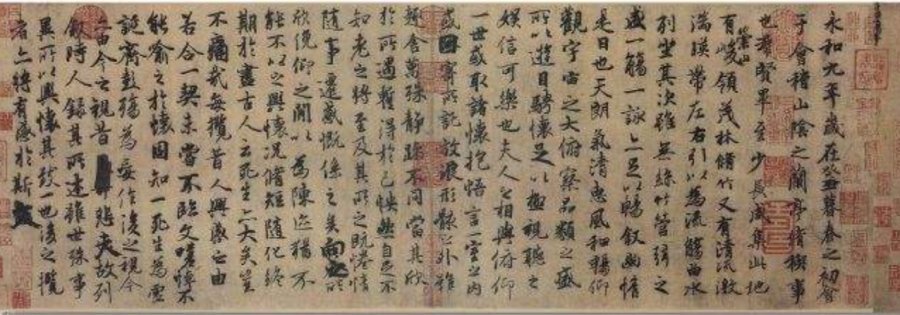
说白了字如其人,就是指书法名家与他的著作类似即创作者的性格特征,字的设计风格接近彻底类似,例如创作者高大魁梧且身型显胖,那麼他的字一般 是豪爽、粗犷,线框雄浑丰满,瘦者则线框苗条等。字如其人,是有科学论证证实的,不但是书法名家的著作字如其人,平常人书写也是如此,只不过是他与书法名家的有所区别,由于手写是人的大脑的形态意识根据手转为笔,换句话说,把手脑的形态意识转到笔端,那麼,哪些的形态意识便反映哪些的笔迹来。
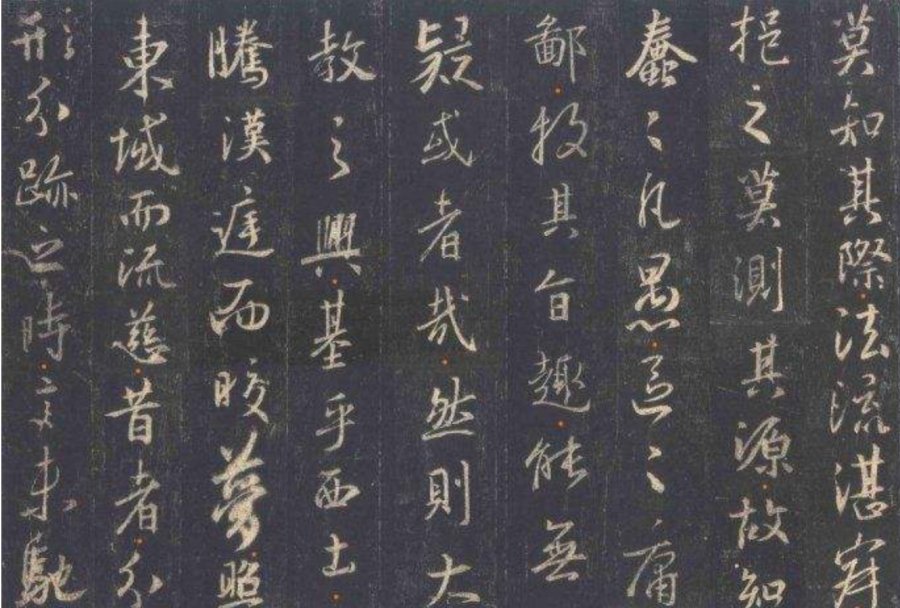
平常人反映创作者的性情仅仅由于大脑这一心电图检查操纵手上的笔流露创作者的创意心迹,自然,凭肉眼是看不出的,由于一般的书写算不上设计风格,只有说他的字里有本人的个性与感情的物品。,一般 平常人书写要根据“评定”才可以明确哪些的性情和感情。例如经评定得到创作者的一些心理活动描写及其性情感情特点等的特性。而书法名家的字一般 不用评定便可右出其个性化(性情)等特性,自然,赏析者务必是具备一定高宽比的造型艺术中关目光及其艺术美学基础理论才可以恰当分辨的。有关书法家作品的字如其人,我觉得有二种状况,一是著作与创作者外貌特征类似,这类状况要相对性广泛些。例如创作者相貌眉目清秀,他的字通常男秀娴雅;另一种是与表面产生差距,如表面温润如玉,但著作气魄磅磚,宛如战马奔腾,一泻千里。如大家看毛主席的字就与表面不是很相符合,可是他的著作两者之间强劲的内心世界一拍即合,名人的风采和思想家扭转局势的魄力,很当然地反映在他的著作中,这也是他心里精神面貌的真实写照。实际上,字如其人特指的不仅是表面特点,还应指创作者心里。
文文弱弱的创作者写成大气磅礴的著作,是由于心里有着的豪情万丈与强劲,及其上善若水的胸襟人生境界。显而易见,真实的字如其人应当就是指创作者本质精神实质与书法字画的设计风格的“地支相害”而成,而表面的字如其人则不可以反映、最少不彻底反映出创作者的精神世界。说字如其人(表面)是种浅部次的“字如其人”,书法艺术的高人生境界是个性化(性情),那麼,仅有著作像创作者本质的精神实质性情,才可以算是上真实的字如其人,而像表面的字如其人则没法反映。从这一方面上讲,书法艺术应是字与其心,并非字如其人。例如,明朝佞臣严嵩,听说看起来眉目清秀,字也写的好,北京市知名的酱制品园六必居的广告牌流传就是他所题写的,笔迹整齐强有力。但内心歪斜,字写的再多又有什么作用。字与其心,通常书法艺术更有性格,书法艺术的性情才可以更强反映,也才可以支撑点个性化的张杨与突显。字与其心,本质便是书法艺术高人生境界的写心、写性、写情。字与其心,便是再用“心”撰写,用“心”写作。